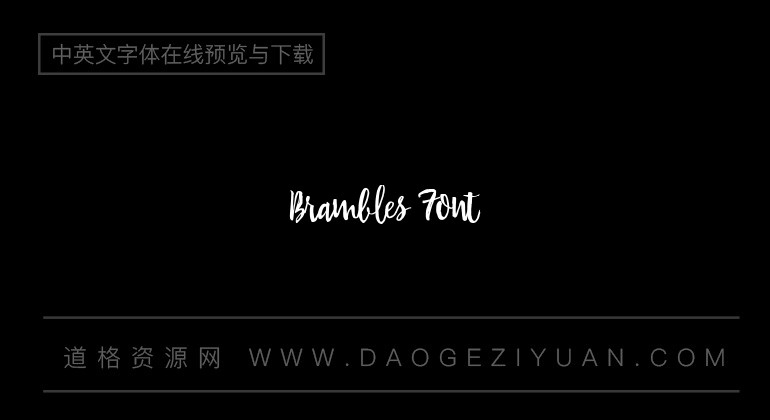
Brambles Font 是一种手写风格的字体,它由英国的设计师 Angie Baldelomar 创作。这种字体的特点是形态不规则,带有手写体的自然感觉,同时也具有一定的艺术气息。 Brambles Font 的字母形状有些像枝条,这也是这种字体得名的原因。它的笔画有时是粗犷有力,有时是柔和流畅,给人一种自然、随意的感觉。这种字体的设计灵感来自于手写字母和草本植物的形态,因此它的字母形状和线条都十分流畅、自然。 由于 Brambles Font 具有良好的可读性和易于识别的特点,因此它常常用于设计卡片、海报、标志、标题等需要突出个性、自然感觉的设计项目。如果您希望设计一些带有手写风格、自然感觉的设计作品,Brambles Font 或许是一个不错的选择。内容介绍
Brambles Font是一款非常不错的手写艺术字体,具有很好的视觉感,适合于文化类的宣传设计、商业类品牌的广告和产品包装设计以及个性化文字排版等较多场景。